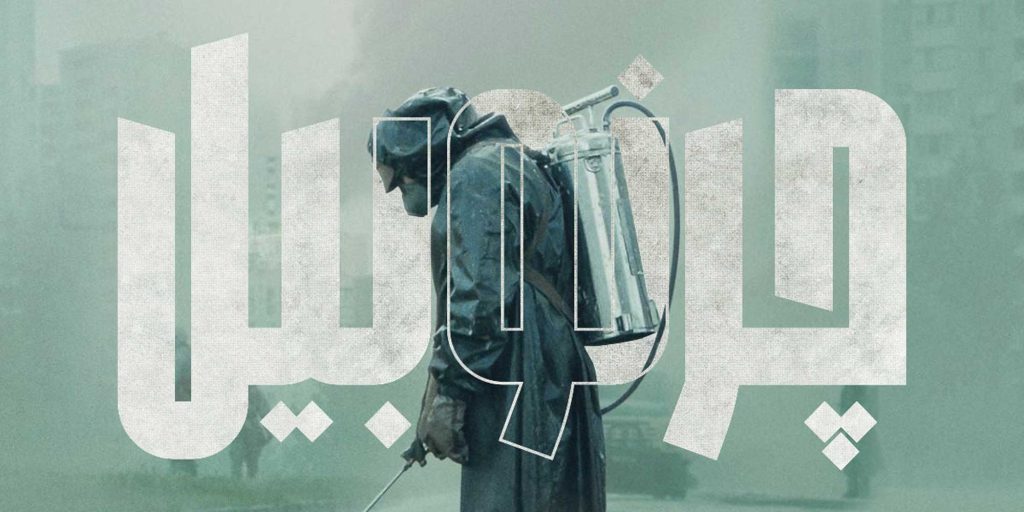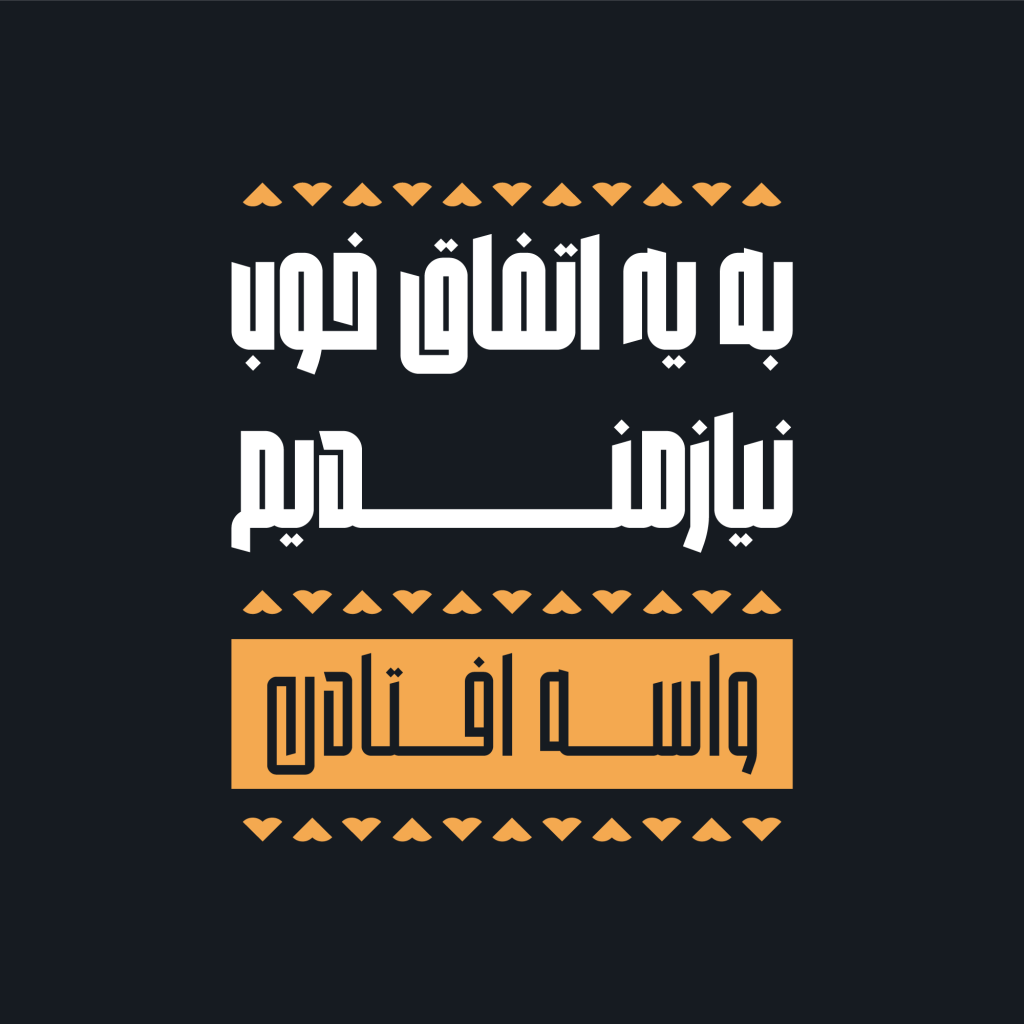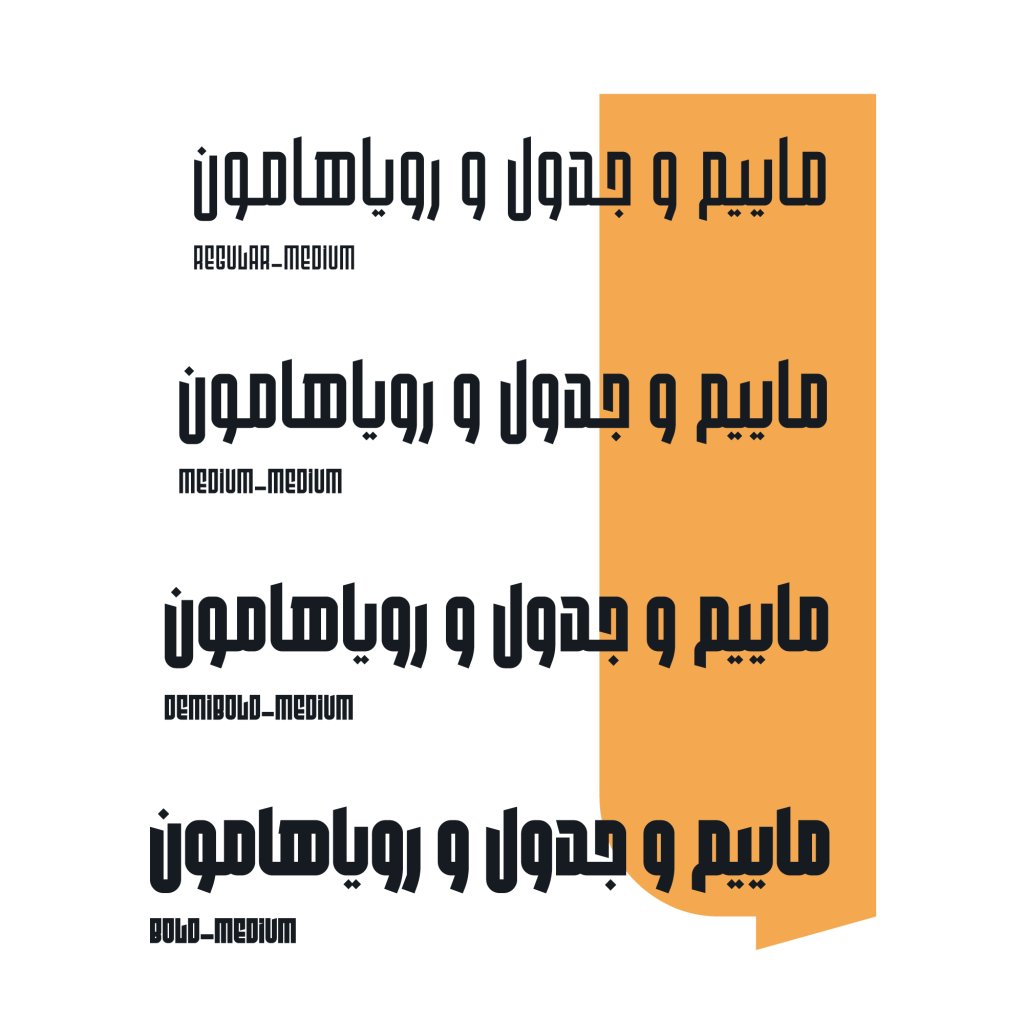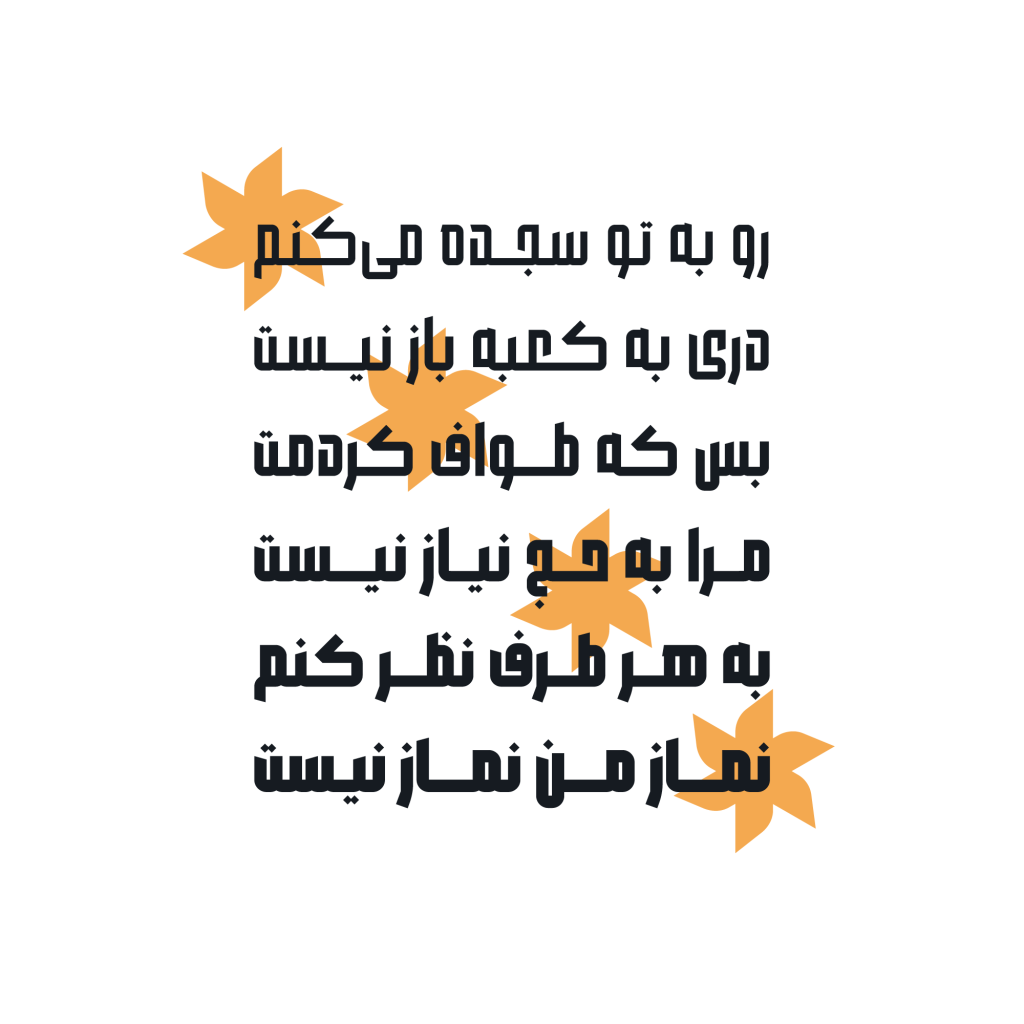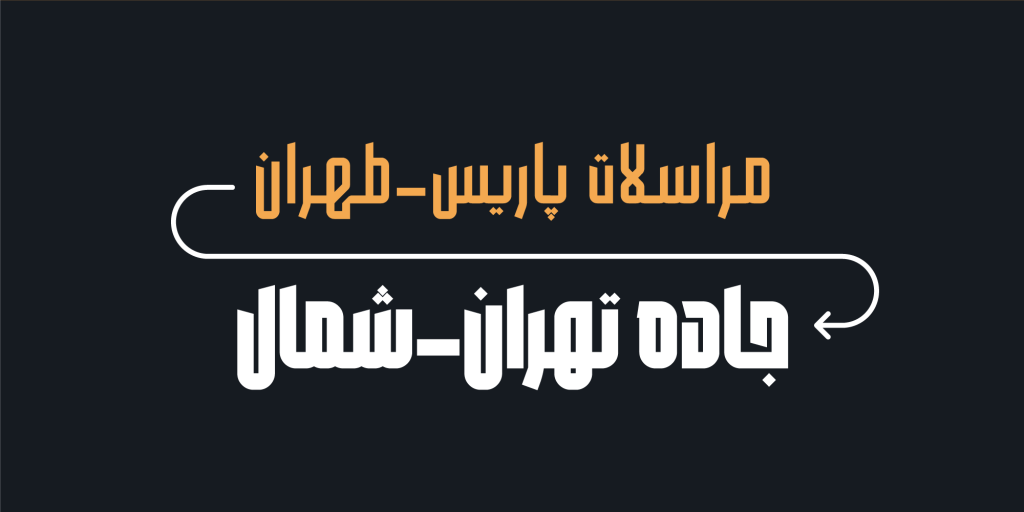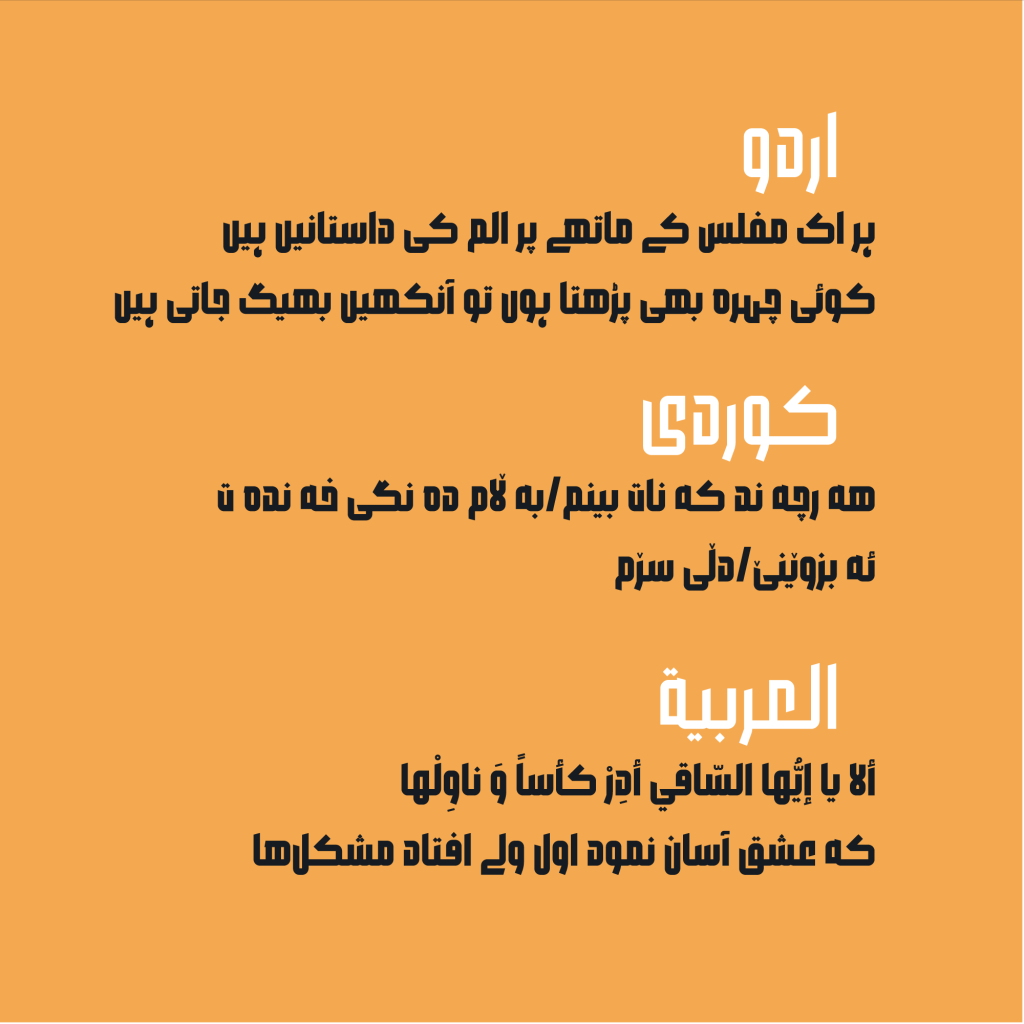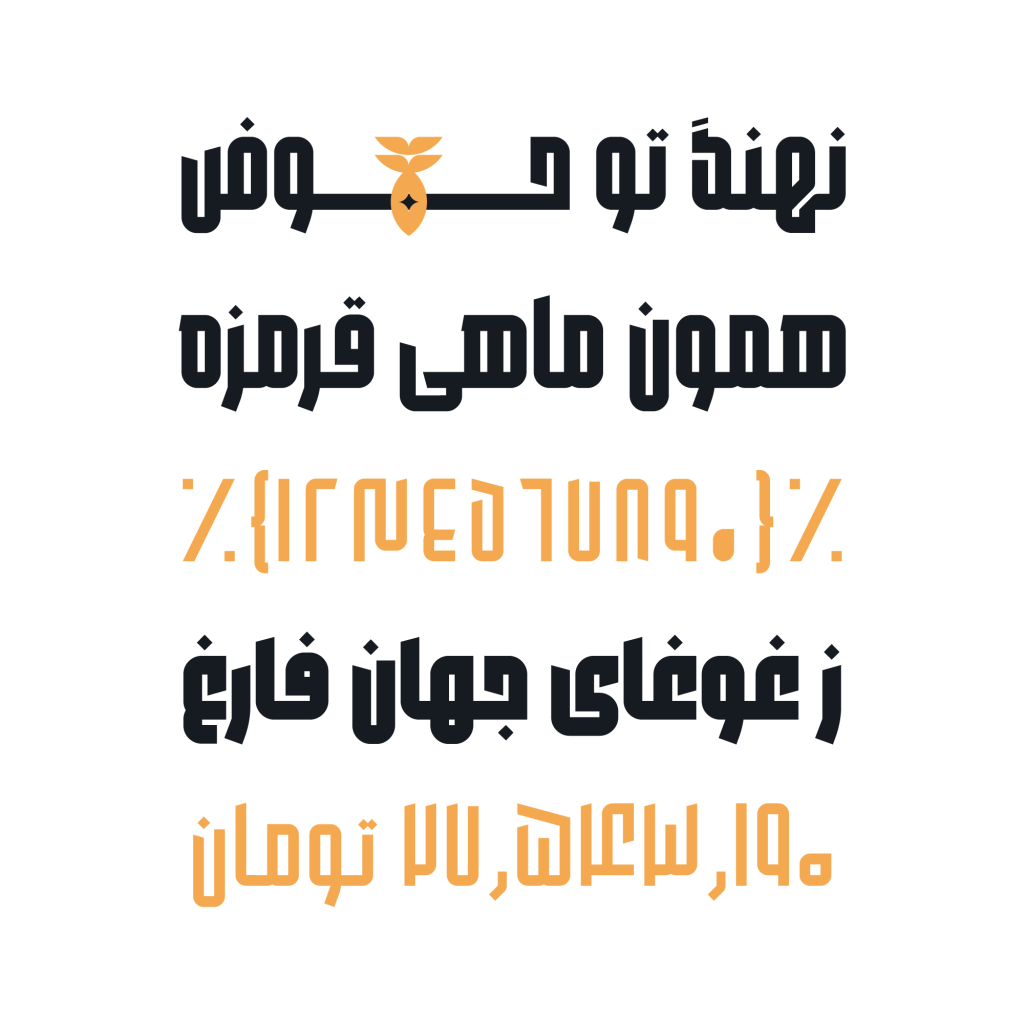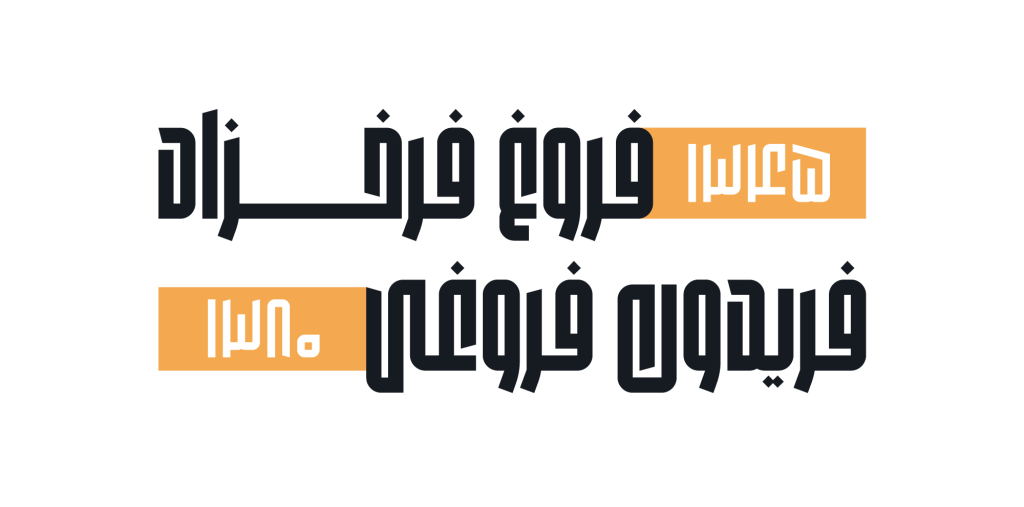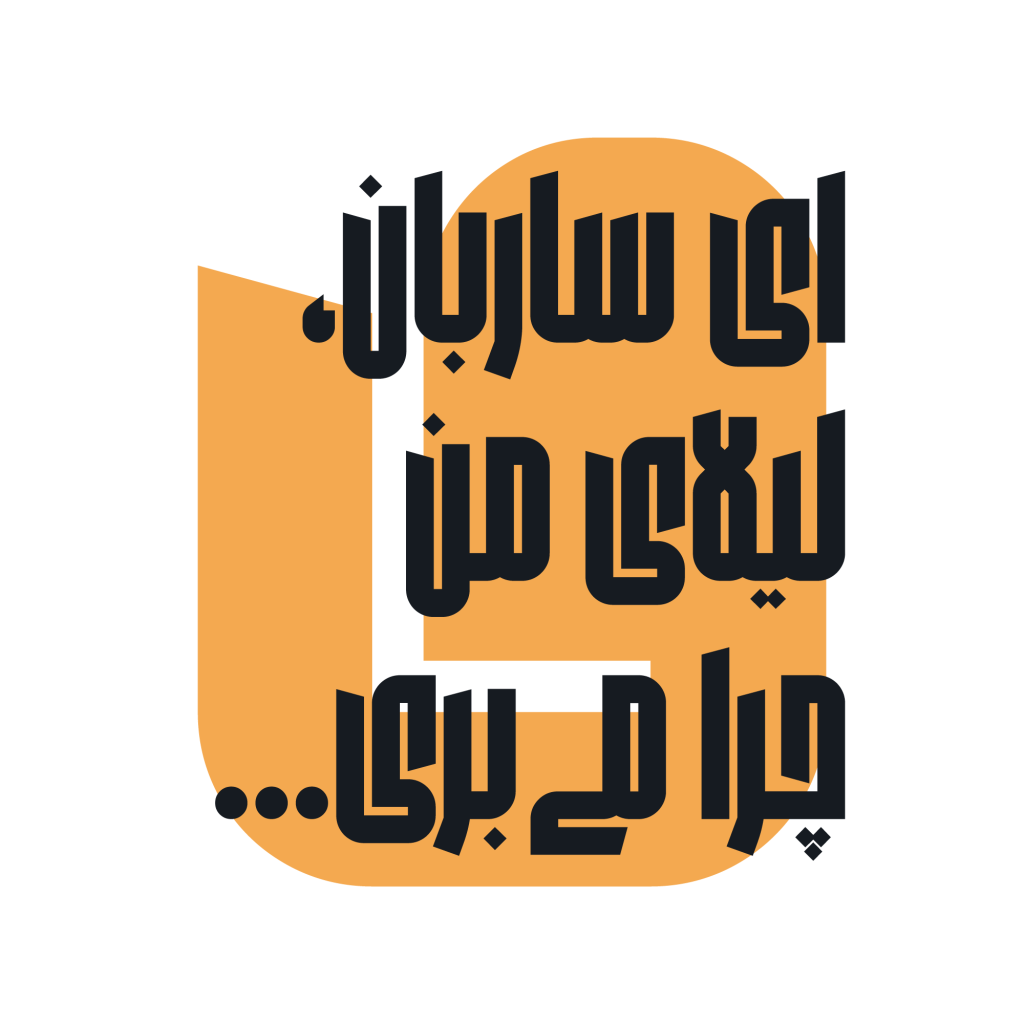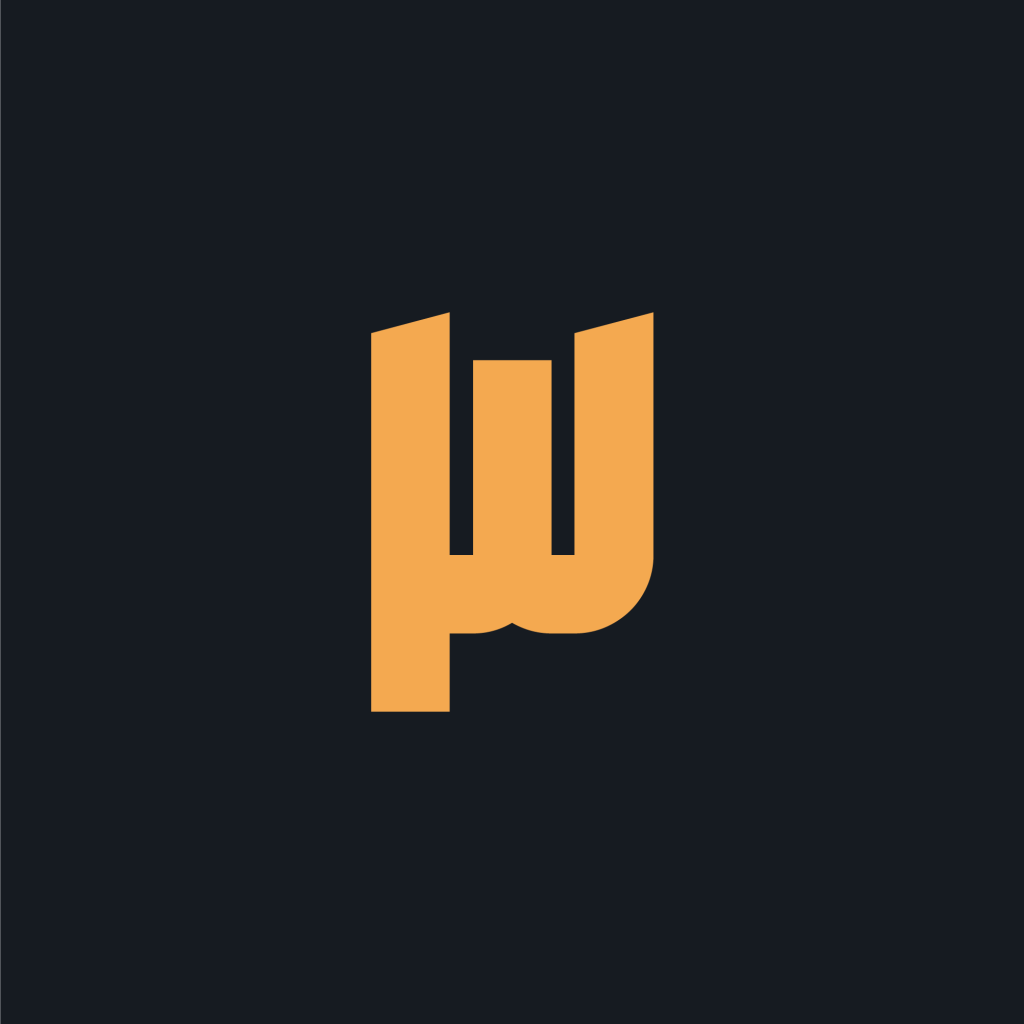
فونت داراب
فونت داراب قلمی که تشکیل شده از یک خانواده با تنوع وزنی و ارتفاع مختلف ائم از ۴ وزن و ۳ ارتفاع توسط گروهی از طراحان ساخته شده است. در نگاه کلی و در یک جمع بندی مجموعا شما ۱۲ فونت در اختیار دارید. کاملا واضح و مشخص است که فراز ها و فرودها یا به عبارت دیگر فواصل خطوط کرسی در این تایپ فیس از همدیگر دور و فاصله ای قابل تامل دارند.
این قلم از دسته تایپ فیس های منو لاین در سطح است سادگی فرم های طراحی و عدم کنتراست در ضخامت از ویژگی های داراب به شمار می رود.عمدتا از زوایای قائم و کمتر از 90 درجه تشکیل و بعضا هم منحنی هایی منعطف و روان را در شاکله خود دارد. دارای شخصیتی جسور و جدی و مصمم است .
داراب مناسب برای متون کوتاه و عناوین و تیتر های تبلیغاتی و مطبوعاتی است حتی شاید بتوان از آن برای لوگوتایپ نیز بهره برد. کاربرد آن وسیع می باشد از دنیای وب و دیجیتال گرفته تا صنعت نشر و چاپ . می توان در پوستر ها جلد کتاب ها مجلات و بیلبورد های تبلیغاتی و پست ها و استوری های شبکه های مجازی و …. از آن کمک گرفته و استفاده نمود
داراب و پشتیبانی از نسخه وریبل varible
شما با دانلود داراب صاحب نسخه وریبل variable نیز می شود که سبب کاهش حجم و افزایش سرعت در صفحات وب است که به راحتی می توانید وزن و ارتفاع آن را با سلیقه خود تغییر و انتخاب نمائید. ویژگی نمایشی که در دل این تایپ فیس وجود دارد سبب جذب نگاه مخاطبین و بینندگان به آن می شود.
فارسی ، انگلیسی عربی، انگلیسی، اردو و کوردی
۴ وزن و ۳ ارتفاع
این قلم از زبان فارسی، عربی، انگلیسی، اردو و کردی پشتیبانی میکند.